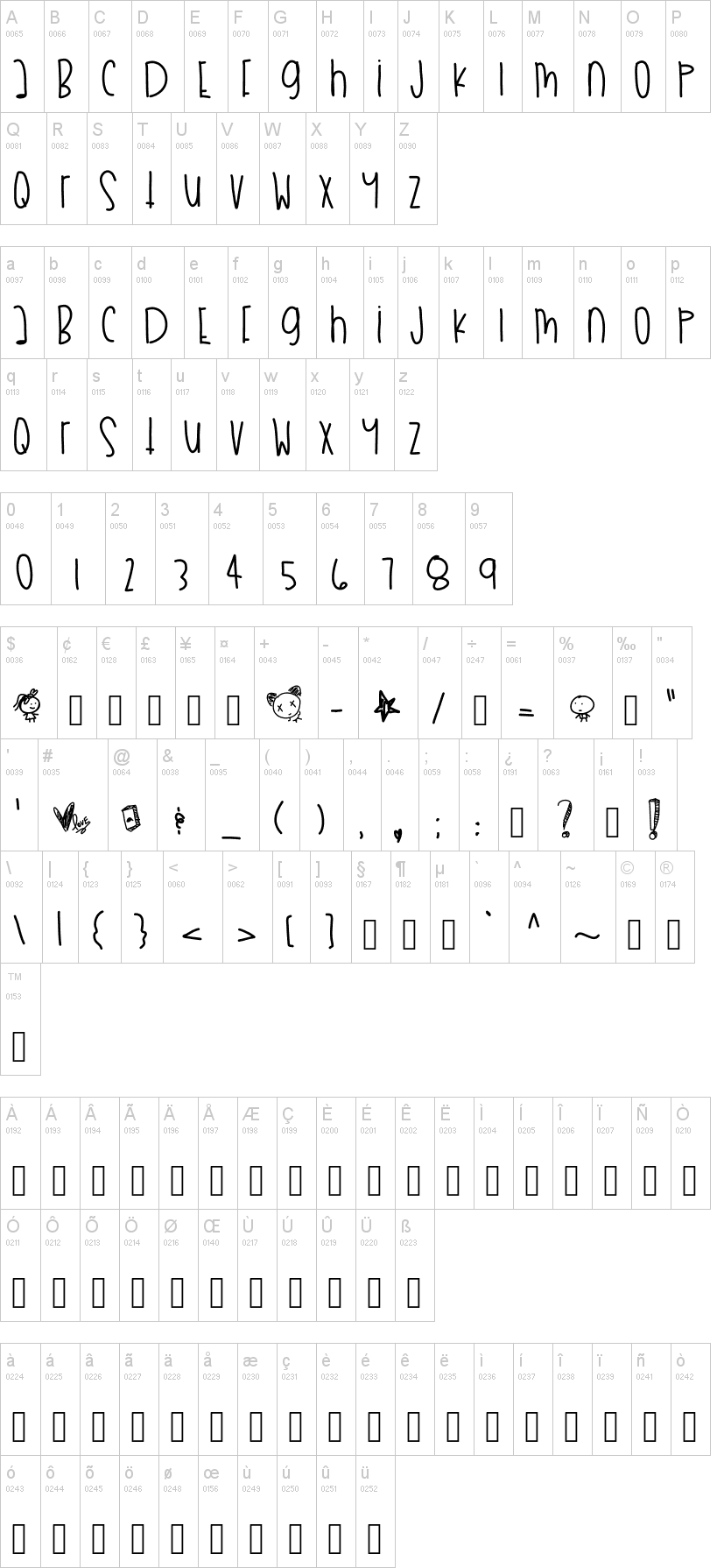
? My Boo Thang 字体是一款浪漫可爱的手写字体,它由美国设计师Crystal Kluge设计。My Boo Thang字体由温柔的笔触和可爱的曲线组成,具有更多的细节和更多的选择,使您的文字更加生动、有趣。它有着优雅的外观,可以用于多种不同的设计,如海报、书籍封面、卡片、海报、网页等。内容介绍
My Boo Thang是一款非常不错的手写艺术字体,具有很好的视觉感,适合于文化类的宣传设计、商业类品牌的广告和产品包装设计以及个性化文字排版等较多场景。